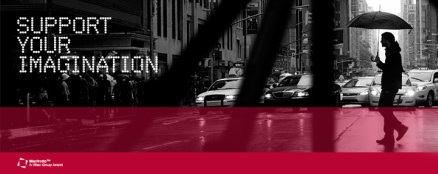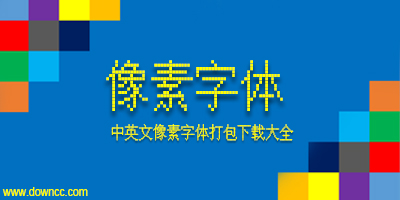
108款精品中英文像素字体合集
108款精品中英文像素字体合集是小编特地为广大设计师精心准备的像素字体包,共有中文、英文像素字体108款,包含了RR_basic像素字体系列,04b像素字体系列、hooge像素字体系列、kroeger像素字体系列、Bus像素字体系列、SG像素字体系列以及难得的几款中文像素,欢迎下载使用。
什么是像素字体
什么是像素字体?引用百度百科的说法就是:像素字体-字体的粗细可以调至一像素,看起来类似利用小方块组成的字体。在小尺寸下仍然能够正常浏览,而不失真的字体……
字体设计的漫长过程中,像素字体代表了一个时代的风格。以前电脑的环境只有低分辨率的显示器,所以像素字体就应运而生了,但是随着时代的发展,现在像素字体已经成为复古怀旧的高度利基风格。
虽然像素字体基本上都是类似积木堆积而成,但很多像素字体依然很有视觉冲击感,有的独具一格,有的赋有浓郁的复古风格。大部分像素字体设置8px依然看的很清楚(其他字体设置为8px就会不清楚)这就是像素字体的特色。
像素字体介绍
1.蒙纳繁圆点阵字库
当 Monotype 公司在1897年发明原文-铁水类型排字机的时候,Monotype公司已经是承诺支持提供最高品质的字型。
Monotype 公司的第一个在中国语言方面的成就要追溯到1920年,蒙纳繁圆点阵字库是当时为印刷中文版"圣经新约"而打造的字体。可能算不上像素字体,应该叫点阵字体吧。
2.最像素EX2
最像素EX2,像素化字体,注册适合ui设计师使用,字体在缩小到10号依然很清晰~
3.方正基础像素字体
方正出品的中文像素字体,不但支持简繁体,还包括藏文、高棉文等,非常不错,不过好像是商业字体
4.在photoshop利用像素字体
有几款中文字体直接可以当像素字体使用,例如宋体,你可以在Photoshop中使用宋体 字体大小为12 消除锯齿方法那里选无,这样打出来的字体就是像素字体形式的,看起来非常清晰(效果可见本文第一副图最上面的文字),也可以使用细明体或新细明体(好像也叫Mingliu或PMingliu)字体大小可以小到11。不过并不是所有的中文字体都适合做像素字体使用。
液晶字体、喷码字体、打码字体
这几款字体不是中文像素字体,不过个人觉得挺实用的,故搜集在一起。
液晶字体、喷码字体(打码字体)比较适用于包装盒上的打码效果字体,或者用于做时尚类的产品海报也非常不错。
5.Zpix中文像素字体
Zpix字体的制作初衷是为了在低分辨率显示设备上取得更好的效果。字体发行格式为BDF,号数为12px(11*11像素),内含26个英文字母+日文五十音+简体中文+正体中文+常用标点符号。